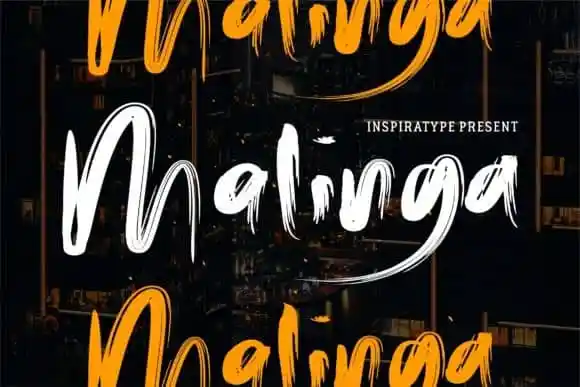
Malinga Brush Font – Download Grátis
A Malinga Brush Font é uma elegante escolha para designers que buscam uma fonte script simples e fluida baseada em letras escritas a mão. Desenvolvida por InspiraType, esta fonte incorpora versões alternativas do OpenType, ligaturas comuns e até mesmo swashes adicionais de cada caractere. Isso permite uma grande liberdade para personalizar as criações dos designers, tornando-a perfeita para aplicar em diversas necessidades como logotipos, cartazes, roupas, etiquetas e muito mais. Com sua simplicidade única e fluida, a Malinga Brush é ideal para aqueles que buscam uma fonte versátil e criativa para seus projetos de design do dia-a-dia ou até mesmo para trabalhos profissionais. Seja você um designer gráfico, ilustrador ou freelancer digital, a Malinga Brush é uma excelente escolha para dar um toque único aos seus designs.